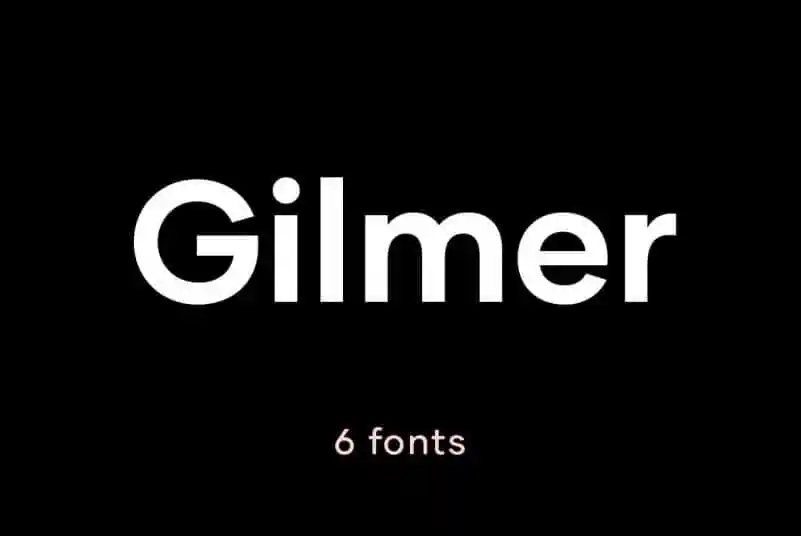
Aqui está uma versão em português do Brasil dos dois parágrafos solicitados, descrevendo a fonte ‘Gilmer Sans Font Family’ de forma envolvente e natural: Esse é um convite para explorar os estilos de uma nova fonte que irá transformar sua composição visual. A Gilmer Sans é uma família de fontes versátil e moderna, com traços elegantes e letrinhas abertas que brilham em aplicativos diversos. Esta família foi projetada pelo designer Piotr Łapa e se destaca pela sua simplicidade geométrica e linha monolítica quase perfeita, um estilo que remonta a famosos tipos de letras como Futura e Avant-Garde. A Gilmer é conhecida por ter uma grande medida da x-height (a altura do conjunto entre as linhas), formas geométricas precisas, cantos retos e contraste estilizado dos traços, características que foram incorporadas aos neo-grottescos da década de 20. Como fonte geométrica e sans-serif, a Gilmer é uma escolha perfeita para o design gráfico em geral – seja para publicações impressas como revistas ou cartazes, identidades de marca robustas, ou até mesmo em sites profissionais. O que torna essa família ainda mais especial é seu enfoque no equilíbrio entre a clássica elegância e um tom moderno. Seja você designer gráfico, publicitário ou editor de conteúdo online, esta fonte oferece opções para estilos variados, garantindo que o resultado final seja tanto belo quanto funcional em uma ampla gama de ambientes digitais e impressos.